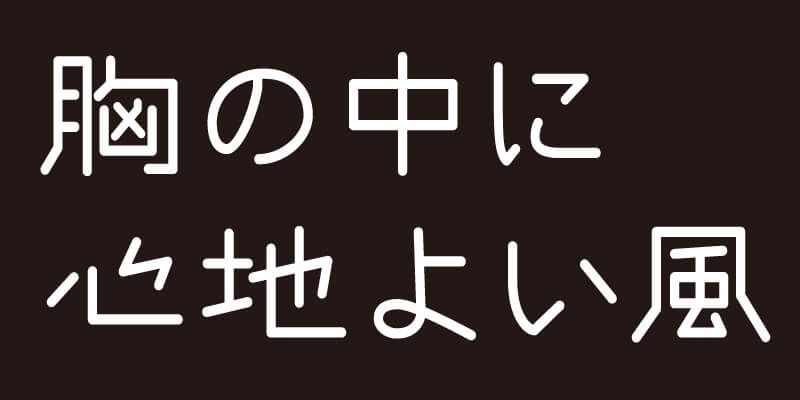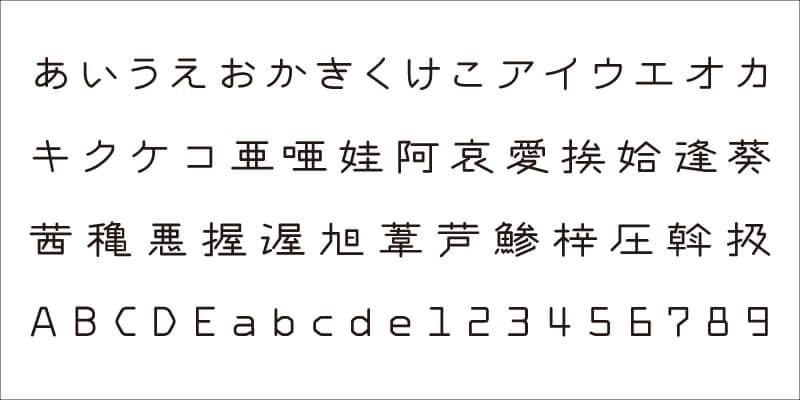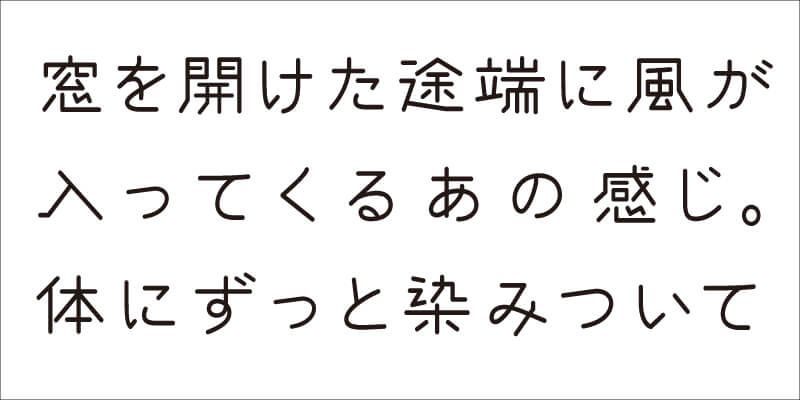
VDL-YotaG ofrece una atmósfera “curativa”, una sensualidad tranquila y un encanto único, con un diseño limpio y nítido. El diseño se caracteriza por elementos de diseño simple y bordes redondeados. VDL-YotaG parece escrito a mano y tiene una gran expresividad. Transmite el mensaje, con una riqueza y matices que confortarán el corazón del lector.
Visual Design Laboratory (VDL) cree en equilibrar la belleza natural de las formas de las letras con estándares rigurosos de legibilidad. VDL ofrece una completa colección llamada “VDL Designers Fonts” (VDLデザイナーズフォント), que seguro va a resonar con diseñadores que buscan un tipo de letra muy individual manteniendo un gran atractivo.